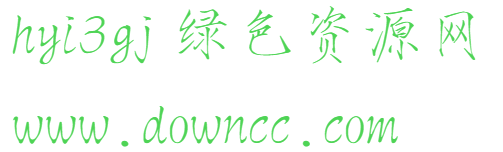
hyi3gj字体又叫汉仪瘦金书字体,该字体笔画瘦劲,线条灵动,颇显风骨,可用于文艺设计、古代影视设计等领域,需要的朋友快来绿色资源网下载吧!
瘦金体是宋徽宗赵佶所创的一种字体,是书法史上极具个性的一种书体,因其与晋楷唐楷等传统书体区别较大,个性极为强烈,故可称作是书法史上的一个独创,因其笔画相对瘦硬,故笔法外露,可明显见到运转提顿等运笔痕迹,是一种风格相当独特的字体。
《楷书千字文》《秾芳诗》《夏日诗贴》《怪石诗贴》《牡丹》《风霜》《大观圣作碑》《神霄玉清万寿宫诏》《瘦金体草书千字文》等。